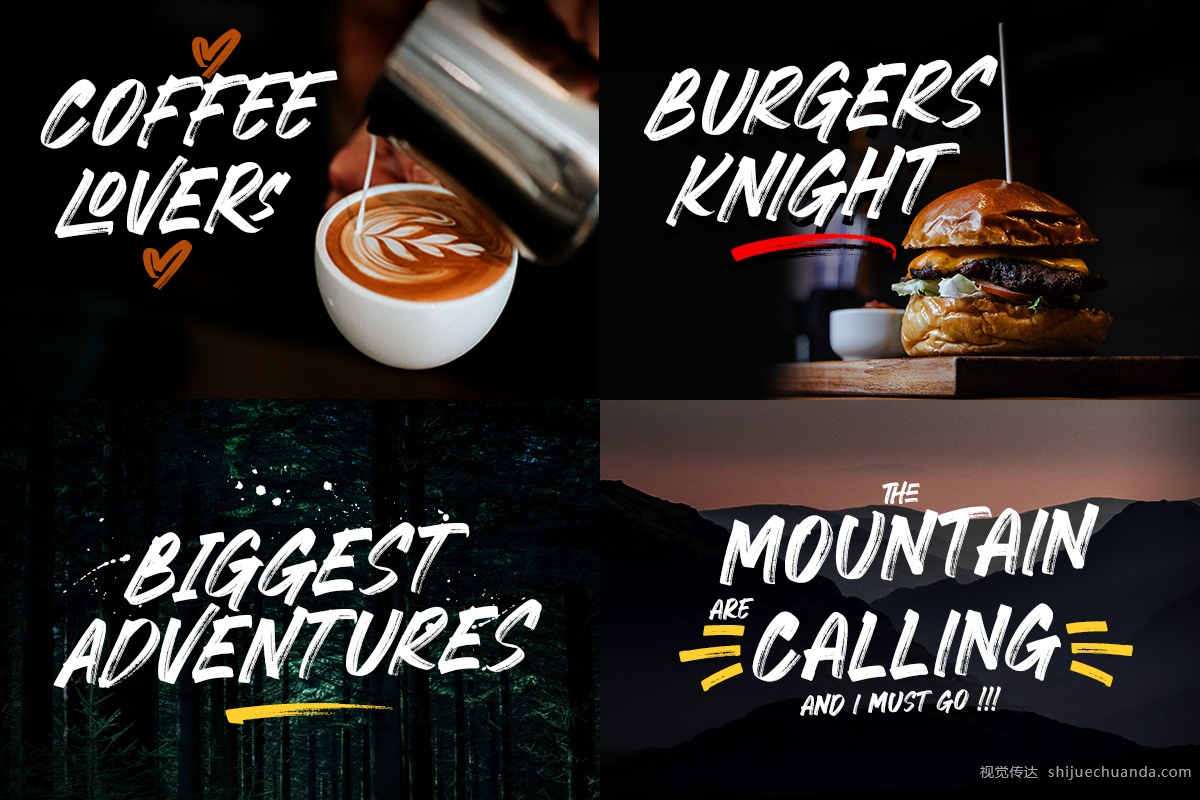
Crackers Brusher字体笔刷,精心制作并充满想象力,粗糙的纹理是这种字体的典型,带有斜线和飞溅,这种字体非常适合挑战性的工作,标题,T恤,网站,连帽衫,以及各种能量的印刷和数字媒体。Crackers Brusher特别注重快速笔触和锐利细节,是徽标,服装,报价,产品包装或任何需要印刷产品的理想选择。